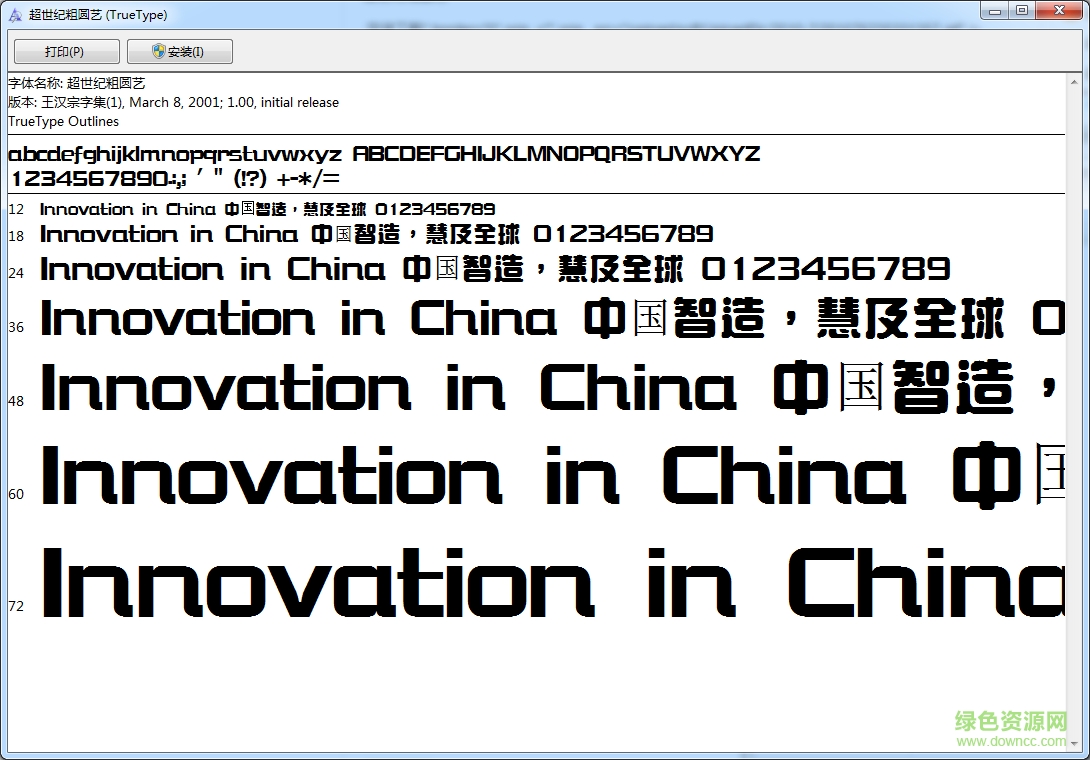
超世紀粗圓藝是超世紀字體庫中一種字體,常用于美工設計方面,喜歡的朋友不要錯過。
審美要的高雅很多。在海報與網(wǎng)站圖標中運用比較多,不適合做正文和標題的選擇,比較適合副標題文字的選擇。
對于設計師的創(chuàng)作來說,每種字體都有其各自的特點與風格。什么情況下采用什么字體、哪類文字適合哪種風格的設計都比較重要,這也是值得思考的!比如無襯線的文字比較適合現(xiàn)代時尚設計中、兒童產(chǎn)品的設計中,粗體比較適合HIPHOP畫面設計中。有襯線的文字的文字一般運用在傳統(tǒng)類、高端類、莊重類設計中等等。在設計中文字最好嘗試一下不同字體所產(chǎn)生的不同感覺。這種感覺需要建立在長期的學習、觀察和思考的基礎上。